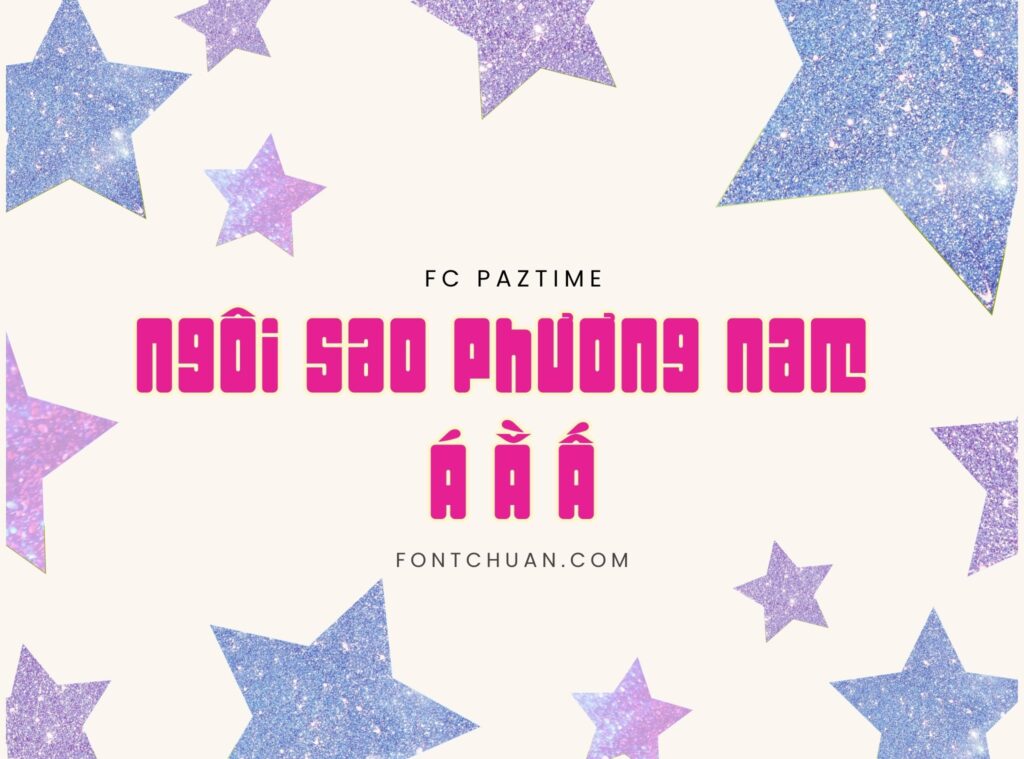
Font “Paztime” là một kiểu chữ độc đáo, được tạo ra thủ công bằng sơn acrylic trên giấy nghệ thuật. Mỗi ký tự trong bảng chữ cái đều có hai phiên bản, cho phép người dùng kết hợp và tạo ra các thiết kế đa dạng. “Paztime” mang lại cảm giác thủ công và nghệ thuật. Font này hỗ trợ đa ngôn ngữ, bao gồm tiếng Việt, giúp người dùng dễ dàng áp dụng trong các dự án sáng tạo của mình.
Về đặc điểm thiết kế, Font FC Paztime Việt Hóa sở hữu các ký tự với nét dày mạnh mẽ phong cách vintage, tạo nên sự thu hút và ấn tượng cho người xem. Font này phù hợp cho nhiều ứng dụng như thiết kế thương hiệu, bao bì sản phẩm và các ấn phẩm truyền thông khác. Các ngành nghề như thiết kế logo, ngành quảng cáo, thiệp cưới, ẩm thực và giáo dục có thể tận dụng “Paztime” để tạo ra những sản phẩm ấn tượng và chuyên nghiệp.
Bên cạnh đó, trong các dịp lễ tôn vinh thầy cô, người dùng có thể dùng Font FC Paztime để làm Font ngày Nhà giáo Việt Nam. Để tạo ra các ấn phẩm tri ân trang trọng, vừa nghệ thuật vừa mang ý nghĩa sâu sắc.
Đặc biệt, nhờ phong cách thủ công và cảm giác nghệ thuật độc đáo, Paztime còn rất phù hợp làm font chữ Trung Thu cho poster, thiệp mời, hộp bánh hay banner lễ hội, giúp thiết kế vừa mang nét cổ điển vừa gợi không khí ấm áp, gần gũi.